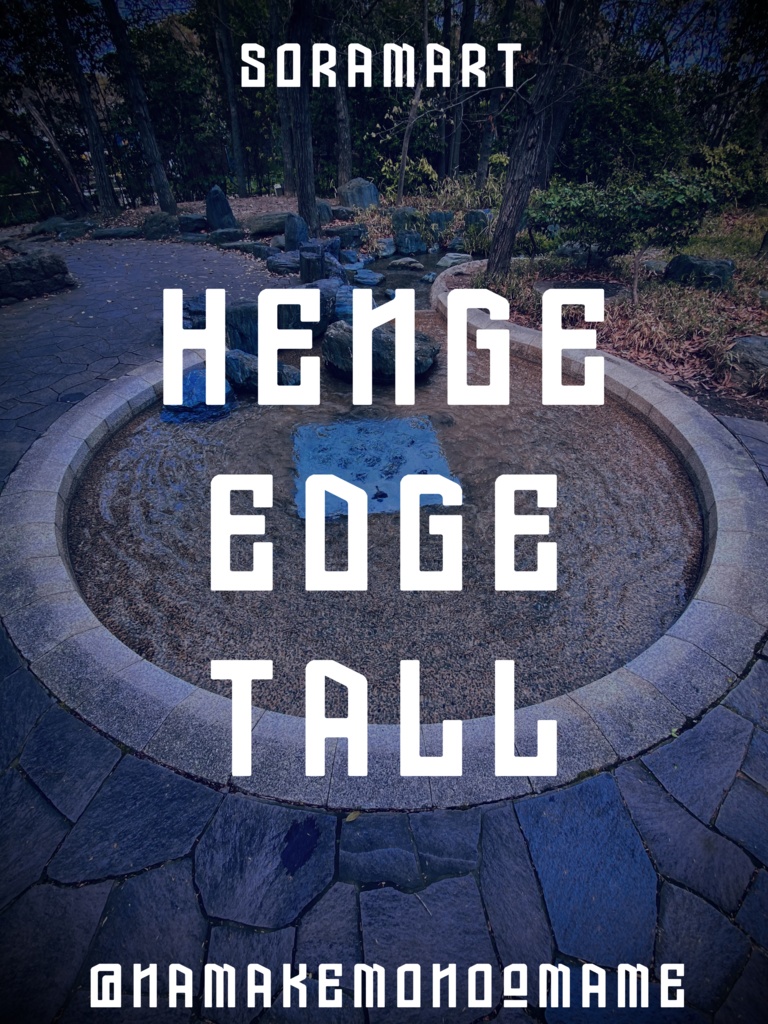
そらマートフォントデータ”Henge Edge Tall”Digital0 JPY무료 다운로드Henge_Edge_Tall.zip (34.5MB)Henge_Edge_Tall.zipAbout Gift”ストーンヘンジ”をイメージした太字縦長フォント "Henge Edge Tall" です。 「TrueTypeフォントファイル」という形式です。 ダウンロードした後、Zipファイル内のデータをインストールしてお使いください。 このフォントは商用利用可となっております。 お客様の制作・創作活動のお役に立てれば幸いです。 ※使用上の注意事項などは、添付のReadmeをお読みください。そらマートVisit FANBOX!Fontsフォントデータ”Hazy Flap”そらマート0 JPYFontsフォントデータ”Amber Nouveau Tight”そらマート2,500 JPYFontsフォントデータ”Amber Nouveau Wide”そらマート2,500 JPYFontsフォントデータ”Amber Nouveau”そらマート2,500 JPYFontsフォントデータ”RANMMA Drive”そらマート2,500 JPYFontsフォントデータ”Dandy Laser Max”そらマート2,500 JPYFontsフォントデータ”Dandy Laser”そらマート2,500 JPYFontsフォントデータ”Bubblegum Beat”そらマート2,500 JPYFontsフォントデータ”Caltrop Serif LLL”そらマート2,500 JPYFontsフォントデータ”Caltrop Serif LL”そらマート2,500 JPYFontsフォントデータ”Caltrop Serif”そらマート2,500 JPYFontsフォントデータ”Tonik Crate Super Long”そらマート2,500 JPYFontsフォントデータ”Dot Eat Bug Acid”そらマート2,500 JPYFontsフォントデータ”Dot Eat Bug Mild”そらマート2,500 JPYFontsフォントデータ”Dot Eat Bug”そらマート2,500 JPYFontsフォントデータ”Solid Voltage Strike”そらマート2,500 JPYFontsフォントデータ”Solid Voltage”そらマート2,500 JPYFontsフォントデータ”Henge Edge Rock”そらマート2,500 JPYFontsフォントデータ”Henge Edge”そらマート0 JPYFontsフォントデータ”Chisel Stroke Wide”そらマート2,500 JPY더보기